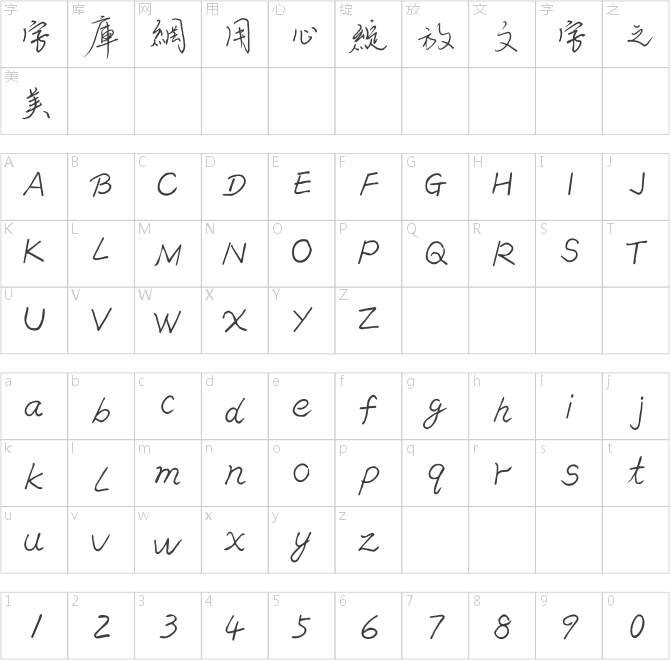
字體名稱: 騰祥巧巧手跡繁
騰祥巧巧手跡繁
騰祥巧巧手跡繁介紹
此款字為騰祥巧巧手跡。書寫一氣呵成,獨具作者自己的風格,無拘無束具有不同的視覺效果,用于正文更體現出手寫自然之感。
騰祥巧巧手跡繁字體TTQiaoQiaoF字庫是一款讓人賞心悅目、百看不厭的中文字體,適合各類廣告和產品包裝設計應用,字體大小10.04MB,格式為ttf字體,上傳用戶是青檸檬,作者/版權方為騰祥字庫